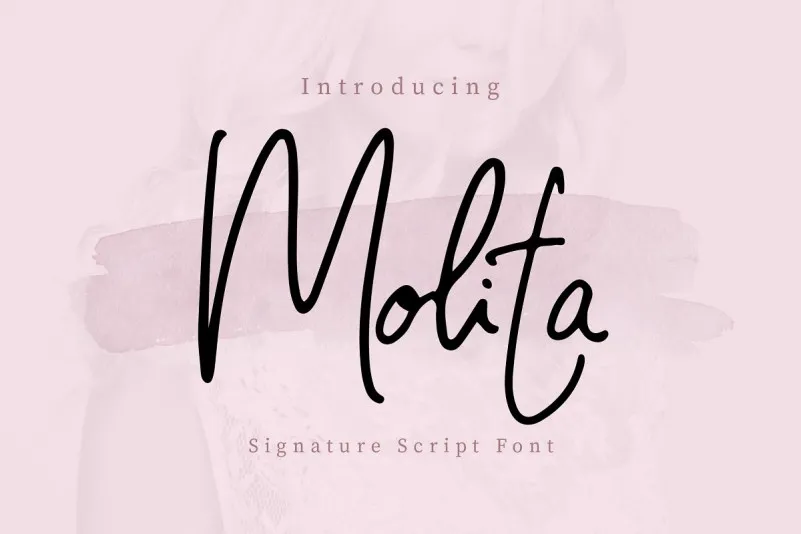
Molita Signature Font é uma tipografia que transmite um estilo elegante de escrita manuscrita contínua. Perfeita para ambientes profissionais e de marca, esta fonte foi criada pelo designer 0001themes e desenhada por peterdraw. Com seu charme suave e perfeição na criação de assinaturas, Molita Signature é uma escolha ideal para qualquer projeto de branding, desde logotipos até embalagens de produtos ou apresentações, oferecendo um toque sofisticado que combina com temas como casamentos e moda. Além disso, serve perfeitamente como overlay de texto para imagens de fundo em estilos elegantes e modernos. Esse fonte é uma ótima adição para qualquer designer gráfico procurando por um estilo criativo e sofisticado para seus projetos.